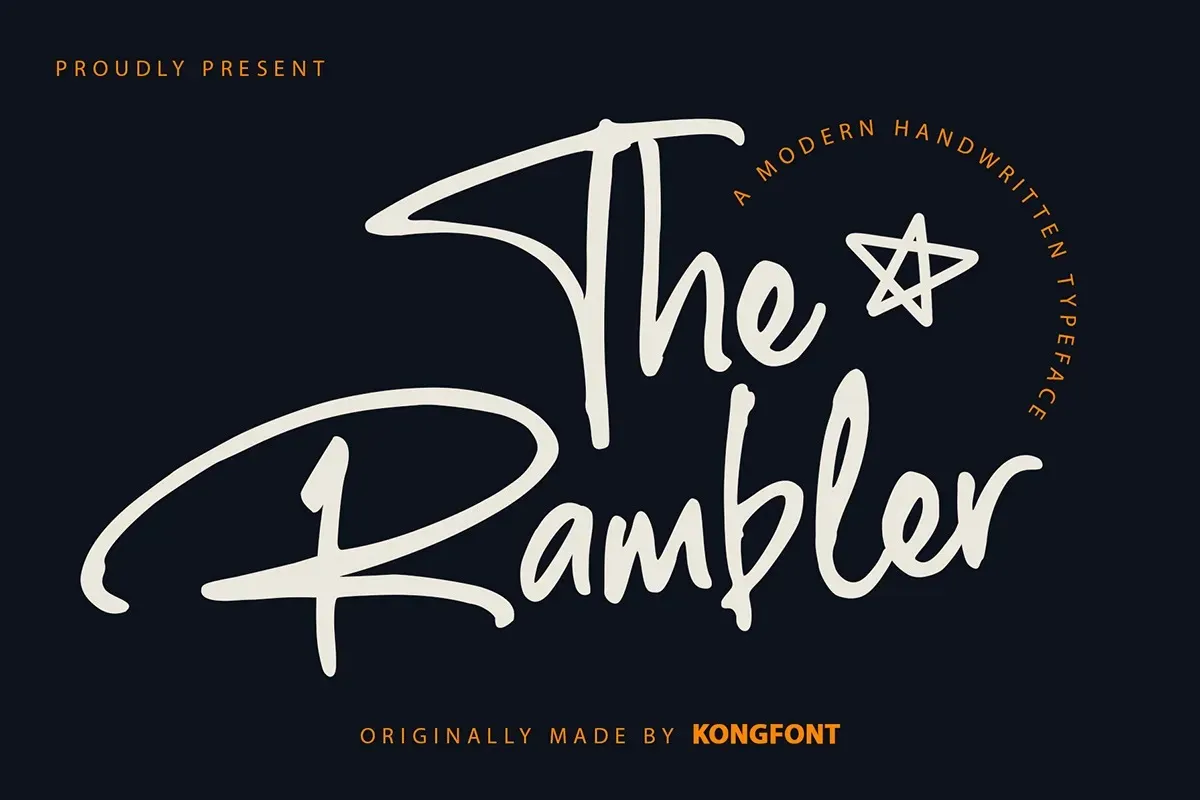
The Rambler Font – Download Grátis
A fonte ‘The Rambler Font’ é uma elegante escolha para quem busca algo delicado mas vigoroso no seu design visual. Criada pela Kong Font, essa tipografia script traz um contraste intenso nas linhas e um tom levemente inclinado, característica que adiciona ao seu charme divertido e versátil. Com ligaturas sutis incorporadas, The Rambler é perfeito para uma variedade de usos gráficos, desde logotipos até títulos de livros, passando por texto em redes sociais ou cartazes de filmes. Suas facilidades na criação de texturas mais longas ou complexas garantem que a The Rambler se destaque em seus projetos, seja um design minimalista em sans-serif ou uma mistura sofisticada com serifas clássicas. Estamos certos de que essa fonte irá transformar sua próxima peça visual em algo ainda mais extraordinário. Não hesite em explorá-la no seu próximo projeto!